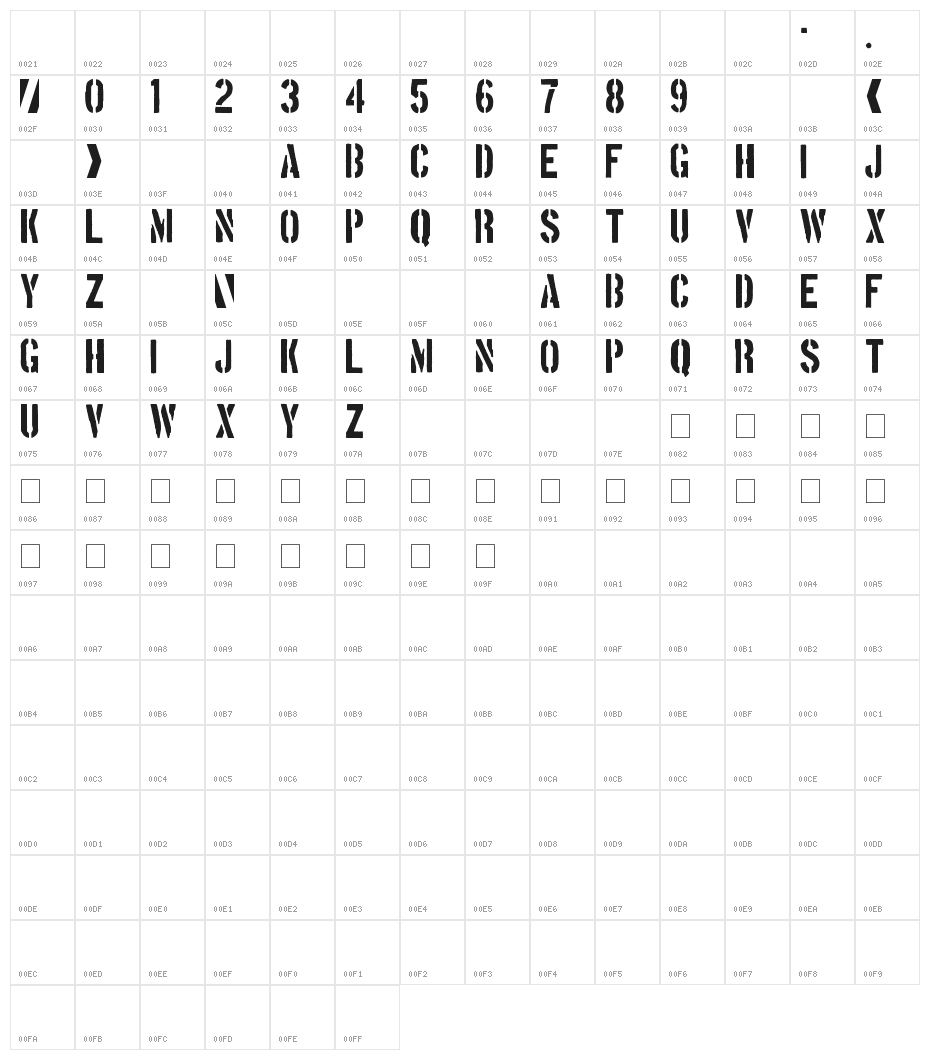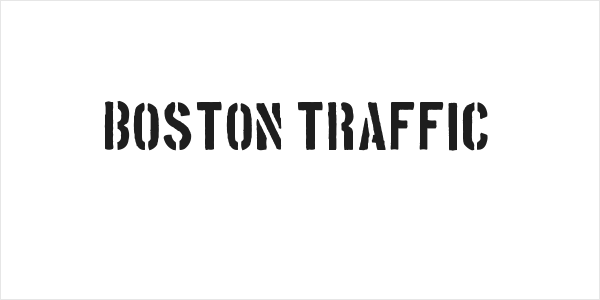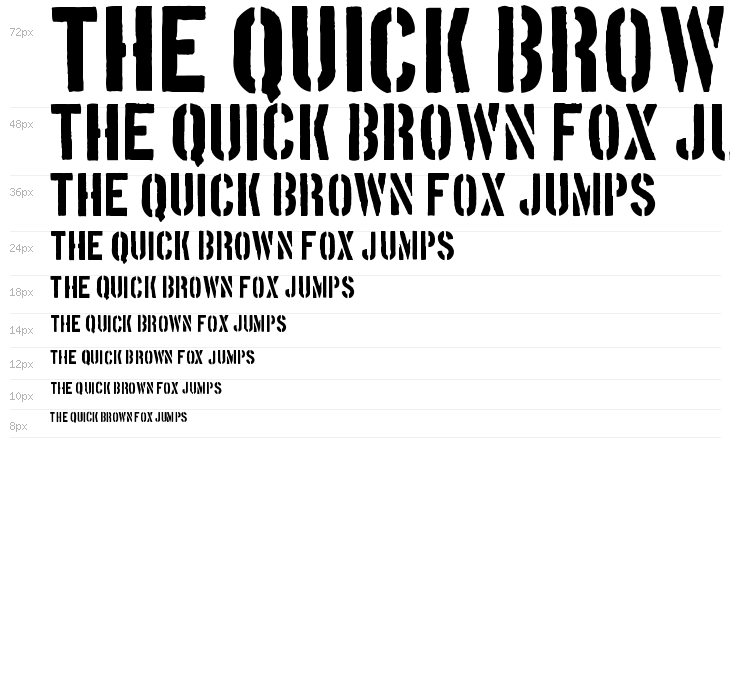
Boston Traffic Font
| Gesamtstil | Industrial, Rugged |
| Anwendungsfall | Headlines, Logos, Signage |
| Vorgeschlagene Projekte | Ideal for use in posters, signage, branding, and any project requiring a bold, industrial look. |